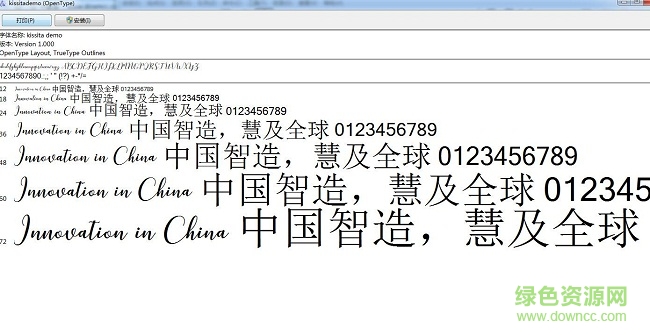
kissita demo
字體筆形介紹
筆形是字體干變?nèi)f化的可變元素,什么風(fēng)格、基調(diào)的筆形,所構(gòu)成的字體也必然地以筆形的風(fēng)格綜合體現(xiàn)。創(chuàng)造出一種新型的字體,塑造筆形是首要關(guān)鍵。
kissitademo字體
字體設(shè)計的基礎(chǔ)
文字是由橫、豎、點(diǎn)和圓弧等線條組合成的形態(tài),在結(jié)構(gòu)的安排和線條的搭配上,怎樣協(xié)調(diào)筆畫與筆畫、字與字之間的關(guān)系,強(qiáng)調(diào)節(jié)奏與韻律,創(chuàng)造出更富表現(xiàn)力和感染力的設(shè)計,把內(nèi)容準(zhǔn)確、鮮明地傳達(dá)給觀眾,是文字設(shè)計的重要課題。